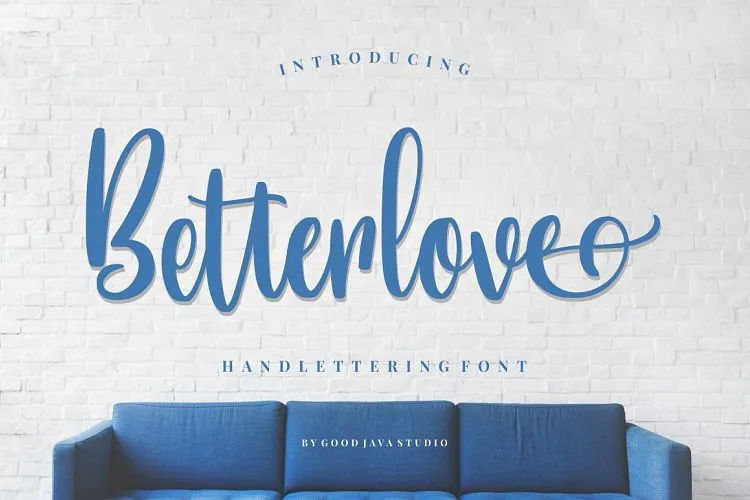
Betterlove Handlettering Font – Download Grátis
Esta fonte ‘Betterlove Handlettering Font’ é uma maravilha de arte que adiciona um toque único a qualquer projeto de design. É uma elegante e sofisticada fonte de script, ideal para invocar o mundo do manuscrito. O designer 24Design criou este trabalho de arte para a Good Java Studio. A fonte incorpora muitas alças nos caracteres iniciais e finais, tornando-os ainda mais expressivos e criativos. Com seu design moderno, essa fonte inclui uma completa coleção de letras minúsculas de coração com alças, números e pontuação. Além disso, vem em opções de ligação aberta e conjuntos estilizados personalizáveis, tornando-a perfeita para uso em cartões de aniversário, monogramas, casamentos, moda, marca ou logotipo. A Betterlove Handlettering Font é uma escolha ótima para aqueles que procuram um toque refinado e personalizado sem abrir mão da modernidade. Ela complementará perfeitamente qualquer projeto visual, transformando-o em algo único e memorável.